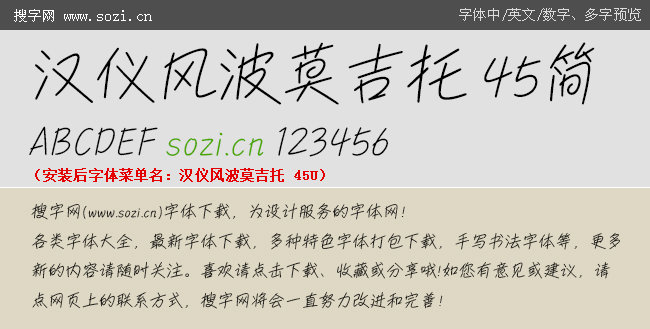
漢儀風波莫吉托 45簡
搜字網(wǎng)給大家提供一款漢儀風波莫吉托 45簡中文字體下載,漢儀風波莫吉托是一款具有獨特藝術(shù)風格的字體,筆畫流暢自然,富有動感和節(jié)奏感。線條的粗細變化豐富,能展現(xiàn)出獨特的韻律。整體風格較為優(yōu)雅,具有一定的文藝氣息,同時又不失現(xiàn)代感。適用于畫冊設(shè)計、海報設(shè)計、包裝設(shè)計等場合使用。(本字體為個人非商用版,如需要商用請聯(lián)系漢儀公司購買版權(quán))
- 風格類別: 手寫書法體